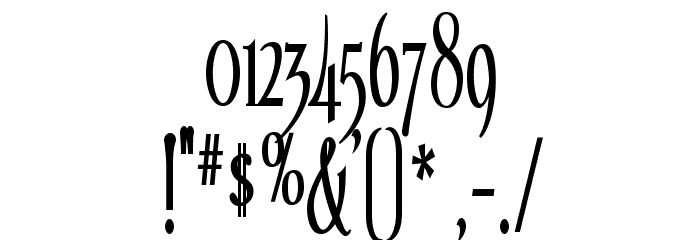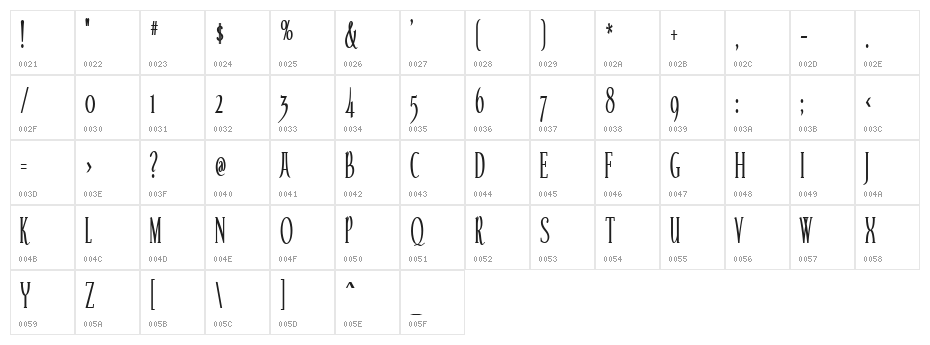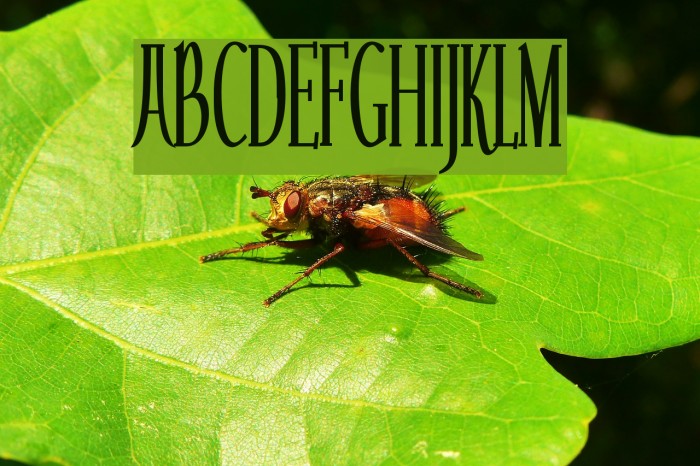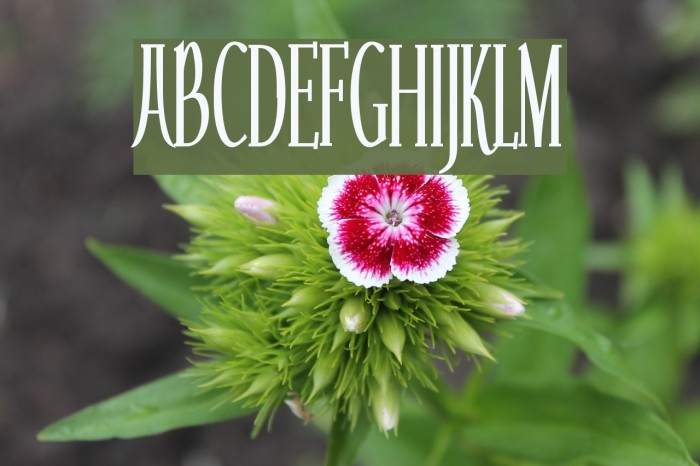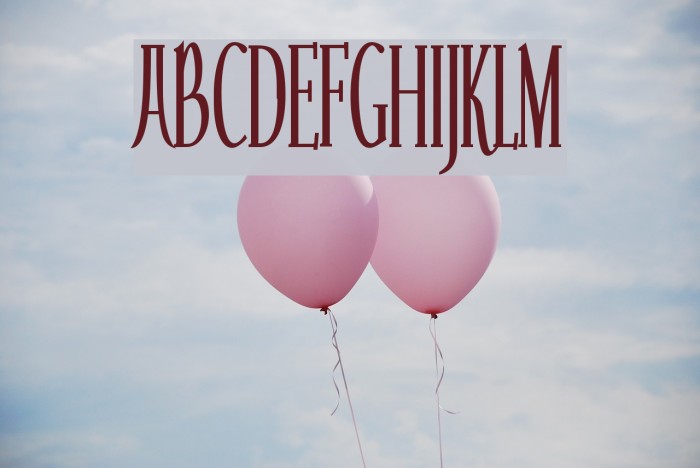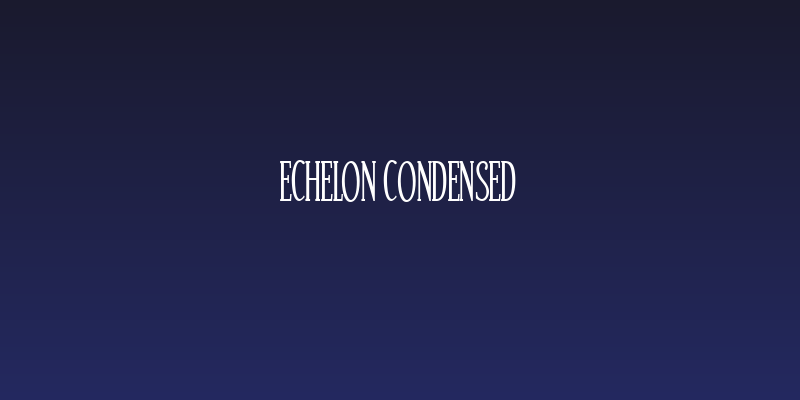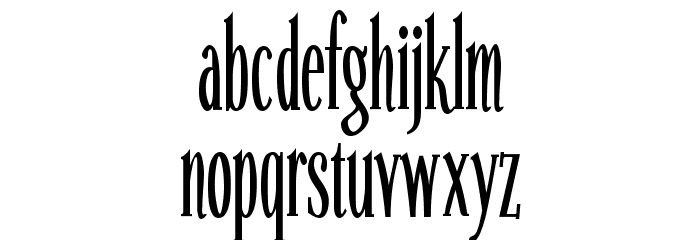
Echelon Condensed Font
| Anwendungsfall | Headlines, Branding, Posters |
| Vorgeschlagene Projekte | Ideal for use in posters, headlines, and branding where a modern, sophisticated look is desired. |
Echelon Condensed